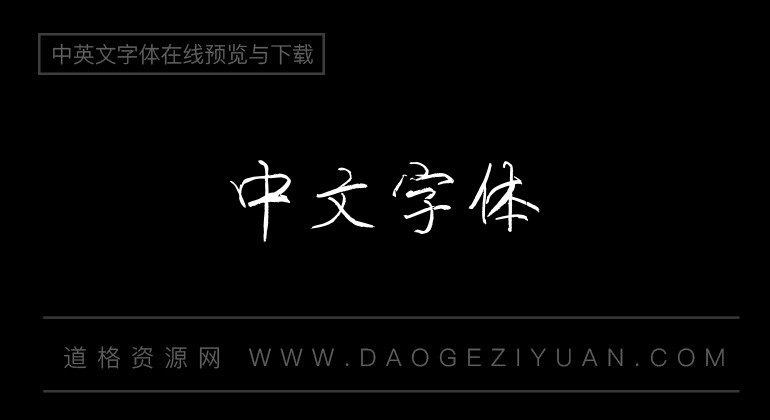
陈代明粉笔体演示版
陈代明粉笔体演示版字体是一款由陈代明设计的中文字体,拥有一种特殊的粉笔体设计,字体简洁大方,更能表达出一种简约的风格。它的特点是笔画流畅,结构紧凑,笔画细腻,笔画精致,笔画优雅,笔画细腻,笔画清晰,笔画稳定,笔画均匀,笔画精细,笔画精致,笔画优雅,笔画清晰,笔画稳定,笔画均匀,笔画精细,笔画精致,笔画优雅,笔画清晰,笔画稳定,笔画均匀,笔画精细。它有助于提高文字的可读性,增强文字的视觉效果,使文字更加清晰,美观。
陈代明粉笔体演示版是一款非常不错的手写艺术字体,具有很好的视觉感,适合于文化类的宣传设计、商业类品牌的广告和产品包装设计以及个性化文字排版等较多场景。